Журнал «Шрифт» • Лучшие шрифты с кириллицей 2014 года по мнению журнала
В этом году мы ещё раз убедились, насколько востребованны сегодня в России знания в области типографики. Совсем немного преувеличив, это можно было бы назвать ажиотажем. С большим успехом в прошлом году состоялись фестиваль «Типомания» и конференция «Серебро набора», стабильно работают существующие школы шрифта, и даже открываются новые. В результате прибавляется число тех, кто получает представление о профессии дизайнера шрифта, и тех, кто пробует свои силы в этой области. Ещё один отрадный факт: почти каждый год на одного выпускника курса Type and Media у нас становится больше. Однако вопреки перечисленным процессам предложение на рынке расширяется едва заметно при вполне предсказуемом качестве шрифтовых проектов. Всё, что появляется в медийном пространстве и вызывает интерес, остаётся недоступным для пользователя либо в виду эксклюзивности проектов, либо из-за неготовности авторов выходить к массовому пользователю.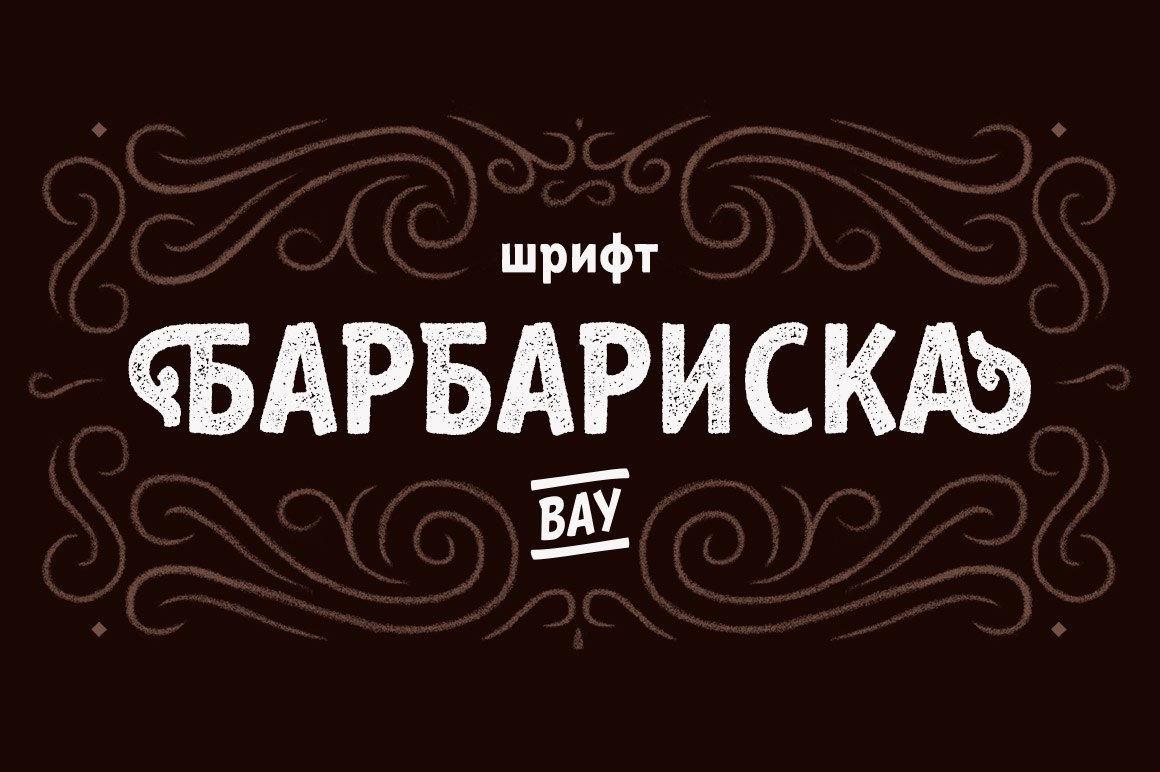
Попробуем дать прогноз. Очевидно, что зарубежные производители будут активнее предлагать шрифты с качественной кириллицей, спроектированной самостоятельно или в сотрудничестве с профильными специалистами. Технический уровень таких проектов будет весьма высоким: разворачивается борьба за экраны, что представляется нам достаточно ёмким рынком. Стоит отметить, что в ушедшем году набрали силы небольшие отечественные словолитни и даже появились новые. Мы ждём свежих проектов от российских компаний и студий Brownfox, Letterhead, «ПараТайп», «Студии Лебедева», новоявленных Contrast Type Foundry и CSTM Fonts наряду с проектами независимых дизайнеров. На этом фоне будет расти спрос не только на дизайнеров шрифта, но и на таких редких специалистов, как шрифтовые технологи.
И наконец, вашему вниманию лучшие шрифты 2014 года. Условия, по которым шрифты попали в рейтинг, с прошлого года не изменились: шрифт должен быть доступен любому желающему для приобретения, обязательное требование наличие в знаковом составе кириллицы, а год выпуска должен быть датирован 2014-м.
«20 копеек» многоликий шрифт. Благодаря остроумной работе с альтернативными знаками он позволяет одним переключением кнопки Stylistic Alternates поменять ощущение от набора. Загляните в состав глифов любого из 14 начертаний (от Thin до Black
Для любителей классификаций, впрочем, карты перепутаны и любые намеки на конкретные исторические гротески являются не более чем иронией (посмотрите на латинские буквы Яркий образец рукописного шрифта с лёгкой отсылкой к готическому письму, с применением широкой кисти.
Набранную этим шрифтом надпись можно принять за леттеринг большое количество альтернативных знаков с росчерками убедительно этому способствует. Вообще, готика в кириллице зачастую выглядит довольно странно и надуманно, но в курсивных конструкциях она обретает не искусственную (как бывает зачастую в прямой фрактуре), а естественную динамику. Заслуживает внимания контроль дизайнера над чёрным и белым и контуром в целом.
Шрифт Formular неогротеск, созданный под влиянием эстетики новой швейцарской волны, где типографика выполняет мощную роль остранения, создавая на своём графическом уровне напряжение между формой и содержанием. Активно разделяя их, Лоренц Бруннер, Симона Коллер, Ронни Юнгер и многие другие «швейцарцы» парадоксально добиваются внимания к содержанию, а в переживший постмодернизм век это, пожалуй, и есть задача номер один для графического дизайнера. Шрифты, которые мы видим в проектах этой эстетики, интересны с точки зрения тонких «сбоев» ритма то на уровне увеличенного межбуквенного расстояния, то на уровне формы отдельных букв.
Новый гротеск Gerbera на первый взгляд отсылает к работам Эдварда Джонстона, Эрика Гилла, Пауля Реннера и Арно Дрешера, к современным шрифтам вроде Euclid (SwissTypefaces) или Brown (Lineto). Сравнивать можно долго и с увлечением, но нам видится в «Гербере» не геометрия «Футуры» и не гибкость форм из эпохи движения искусств и ремесёл, а тень Роже Экскоффона и его гротеска Antique Olive (почему-то сегодня не столь популярного, как перечисленные выше шрифты). Впрочем, это может быть и обманом зрения из-за одной лишь тонкой детали, а именно небольшого обратного контраста в знаках, которому «Гербера» обязана особым ритмом.
Гарнитура Glober на первый взгляд не кажется исключением из ряда открытых узких гротесков, а прилаженные к окончаниям штрихов радиусы скруглений местами выглядят даже немного наигранно. Но потом в поле зрения попадают овалы и полуовалы: они выполнены искусно и формируют характер шрифта именно это меняет наше впечатление от облика гарнитуры.
Овалы «тёплые», не механические: формы букв о, e найдены точно и заставляют равняться на себя все остальные знаки, создавая гамму пластических переживаний в, казалось бы, статичной и бесхитростной модели шрифта. Это сбалансированное шрифтовое семейство примечательно 18 начертаниями от тонкого до сверхжирного, включая наклонные. И, что немаловажно, существуют экранные версии «Глобера» это ещё и универсальный инструмент для разработчика мобильных приложений и веб-дизайнера. Гарнитура победитель конкурса «Современная кириллица 2014» в номинации «Текстовые шрифты».
Шрифтовые проекты Николы Джурека часто связаны с экспериментом, будь то эксперимент технологический или лингвистический. Identitet обернулся новым смелым исследованием и опытом объединения в одной шрифтовой системе нескольких письменностей, которые исторически использовались (и используются) на Балканах.
Это очень высокая планка, поскольку избранные письменности решительно отличаются графическим образом знаков. Глаголица (в трёх начертаниях от аккуратной исторической реконструкции древнейшей «угловатой» глаголицы до более современной круглой), боснийская кириллица, русская кириллица, arebica (вариант арабского алфавита для боснийского языка) и латиница в семье Identitet обладают единой толщиной штрихов, одинаковой высотой строчных и прописных знаков, и так далее во всех деталях, позволяющих достичь единства внутри системы. Identitet проект знаковый для современного мира, охваченного глобализацией с возможностью мгновенного доступа к любой информации, которая, в свою очередь, требует перевода и графического отображения на биллионах мобильных устройств. Никола Джурек провёл серьёзную исследовательскую и художественную работу чего стоит, скажем, создание автором новых графем в версии «круглой» глаголицы для обслуживания звуков в современном сербском языке, которых не существовало в древности.
Победитель, Lapture от Тима Аренса (автор латинской части) и Олега Мацуева (автор кириллической части), 2019 г.